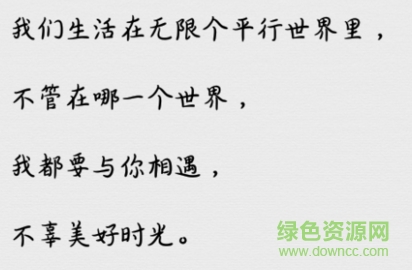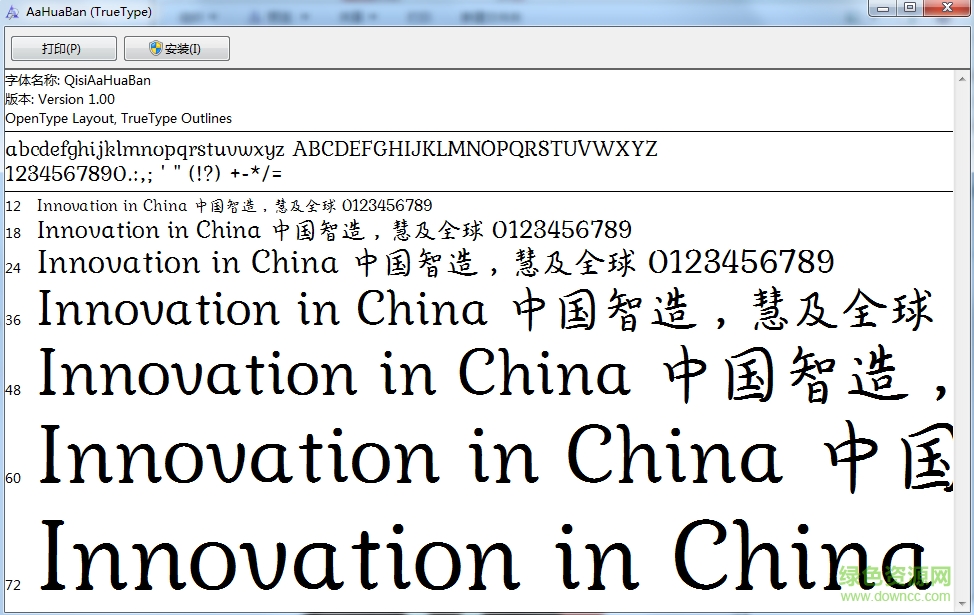
字體管家花瓣體ttf
字體管家花瓣體是一款擁有花瓣浪漫氣息的藝術(shù)字體,清閑簡(jiǎn)黑的模板方便您的文字閱讀和觀看,給你最佳視覺呈現(xiàn),綠色資源網(wǎng)友情提供,歡迎下載使用!
字體管家花瓣字體介紹
花瓣體是字體管家手機(jī)端中的一款書法字體,字跡輕松活動(dòng),粗度和黑度合適,方便用戶的觀看和視覺體驗(yàn)。
花瓣字體